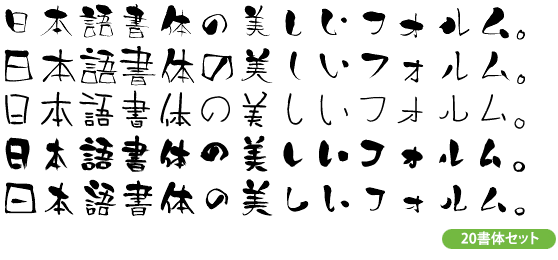
デザイン毛筆
株式会社白舟書体
阿吽 (阿吽M/Uセット)
阿吽(あうん)』はゴシック体と筆文字を融合させた、コラボレーション書体、ハイブリッド書体です。堅い角ばった部分と柔らかい筆文字が、阿吽の呼吸で調和したものであるところから「阿吽」と命名しています。
ゴシック部分の太さが異なる「阿吽U」と「阿吽M」の2書体を収録。